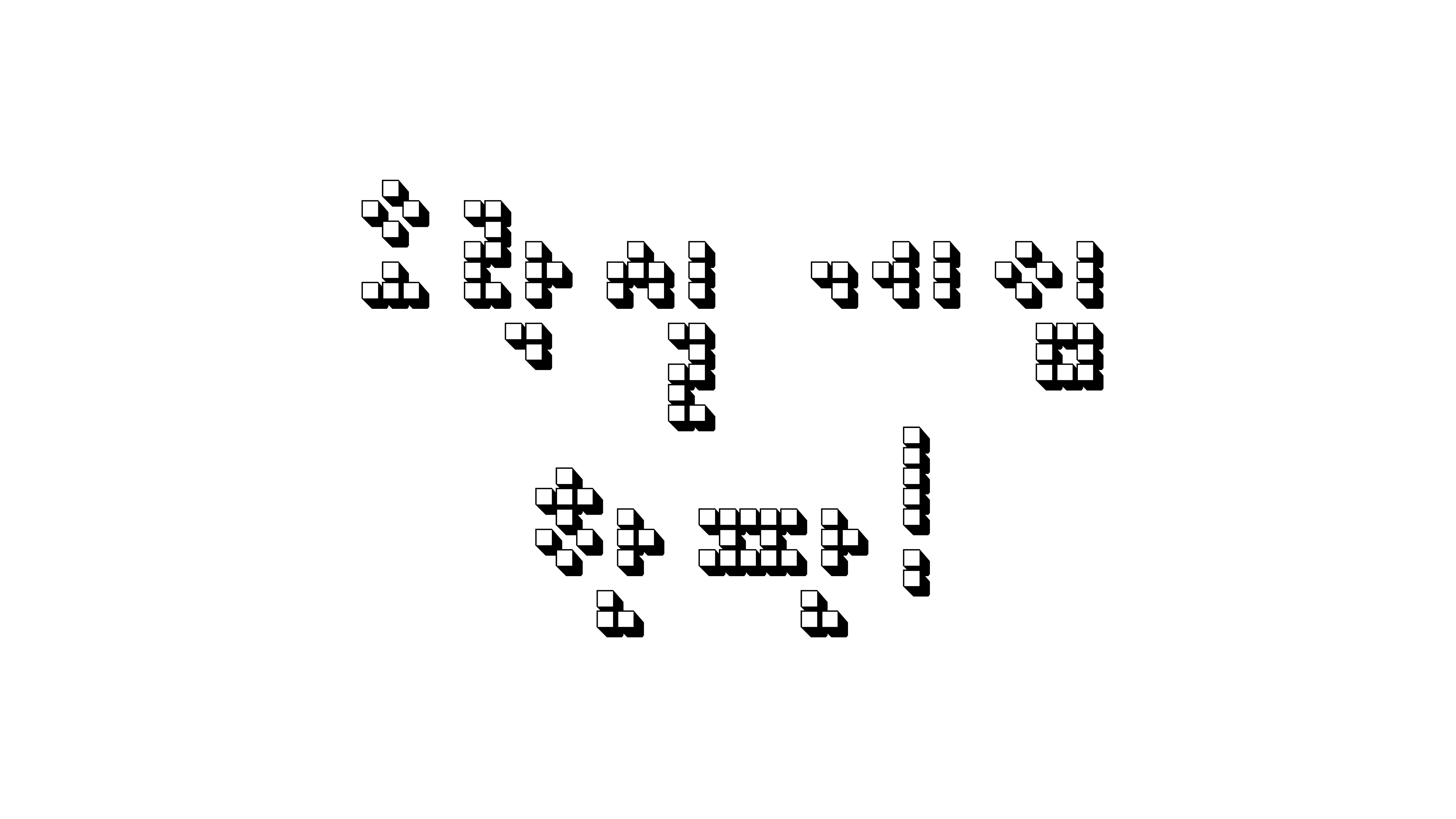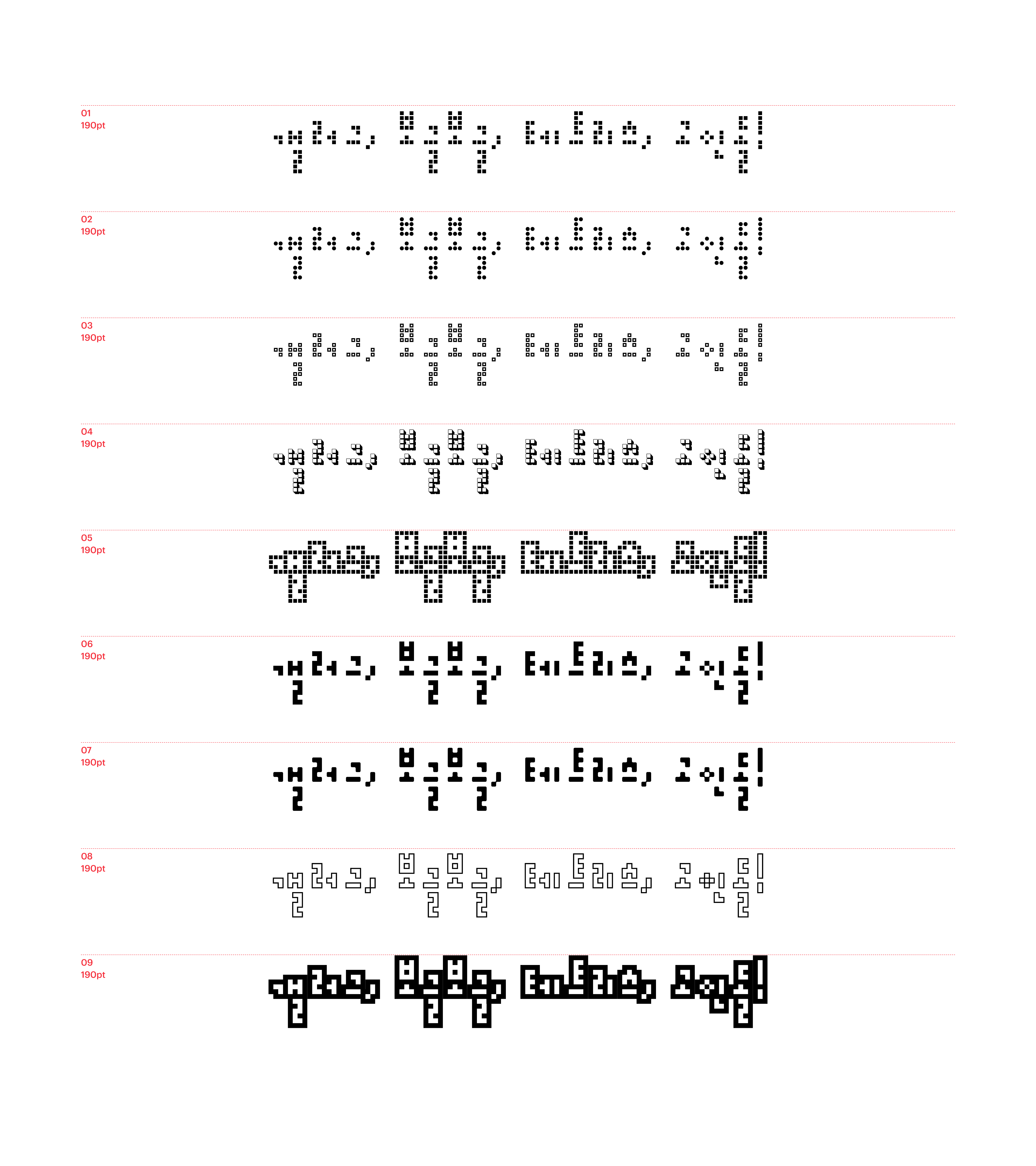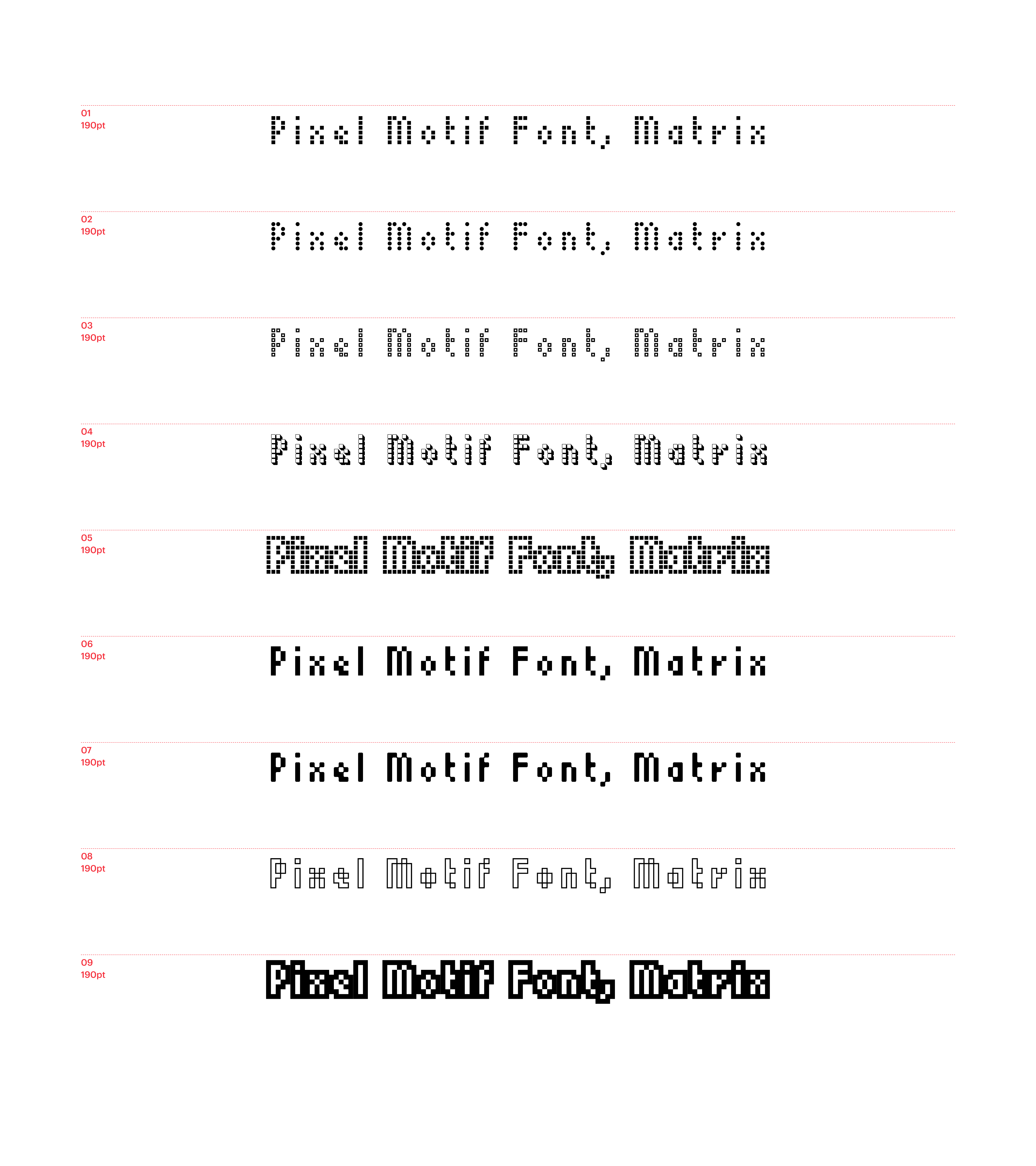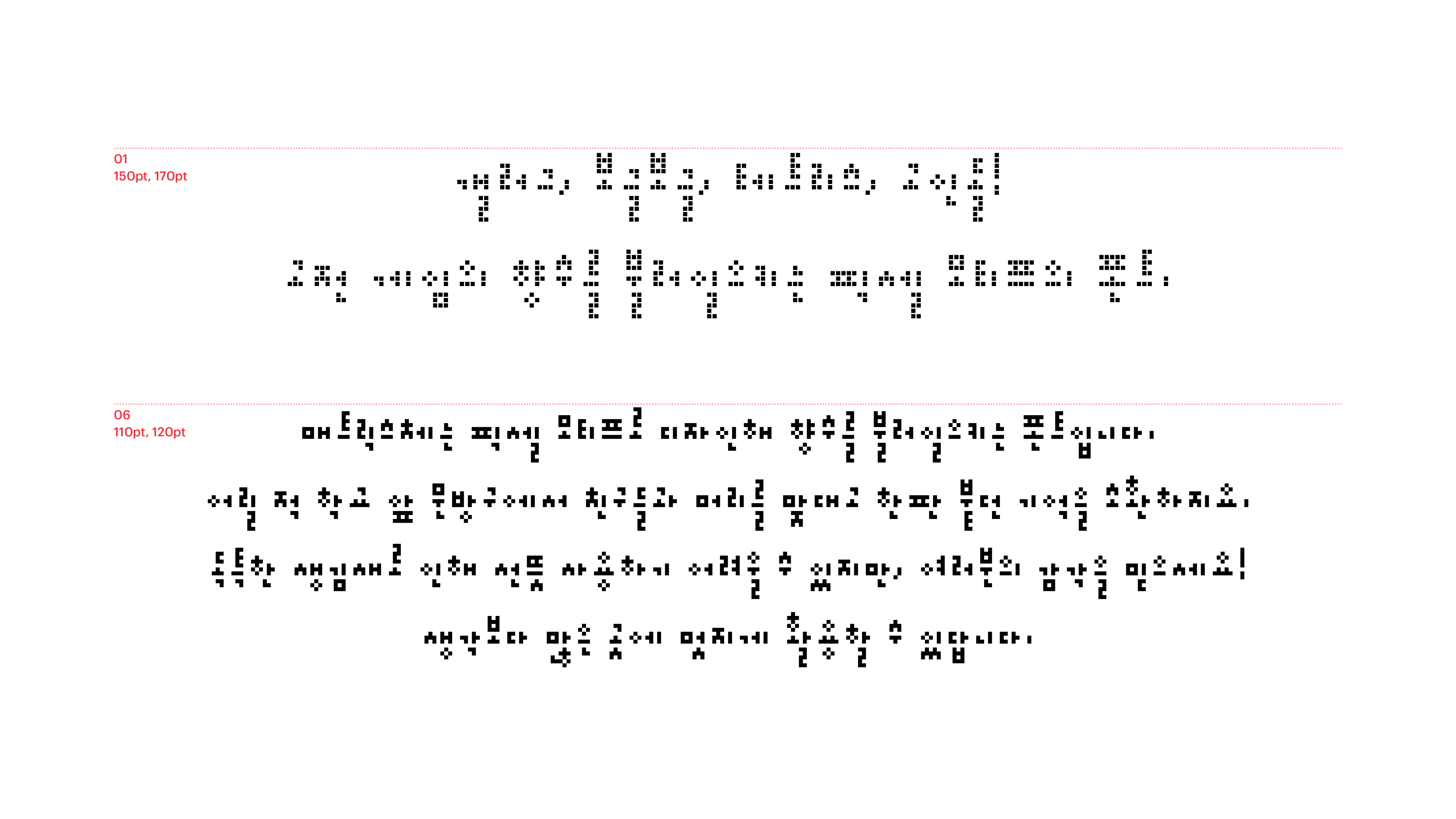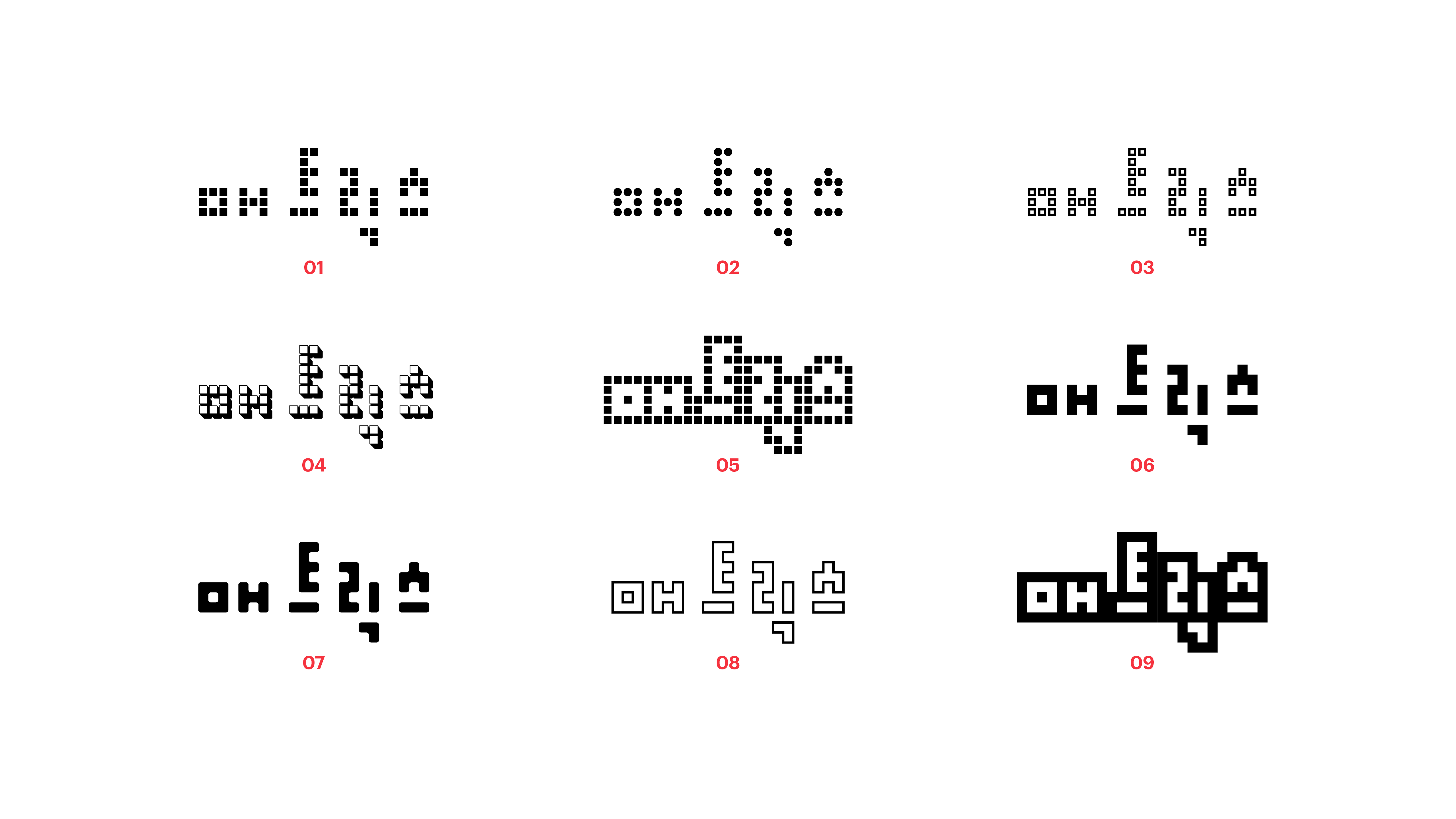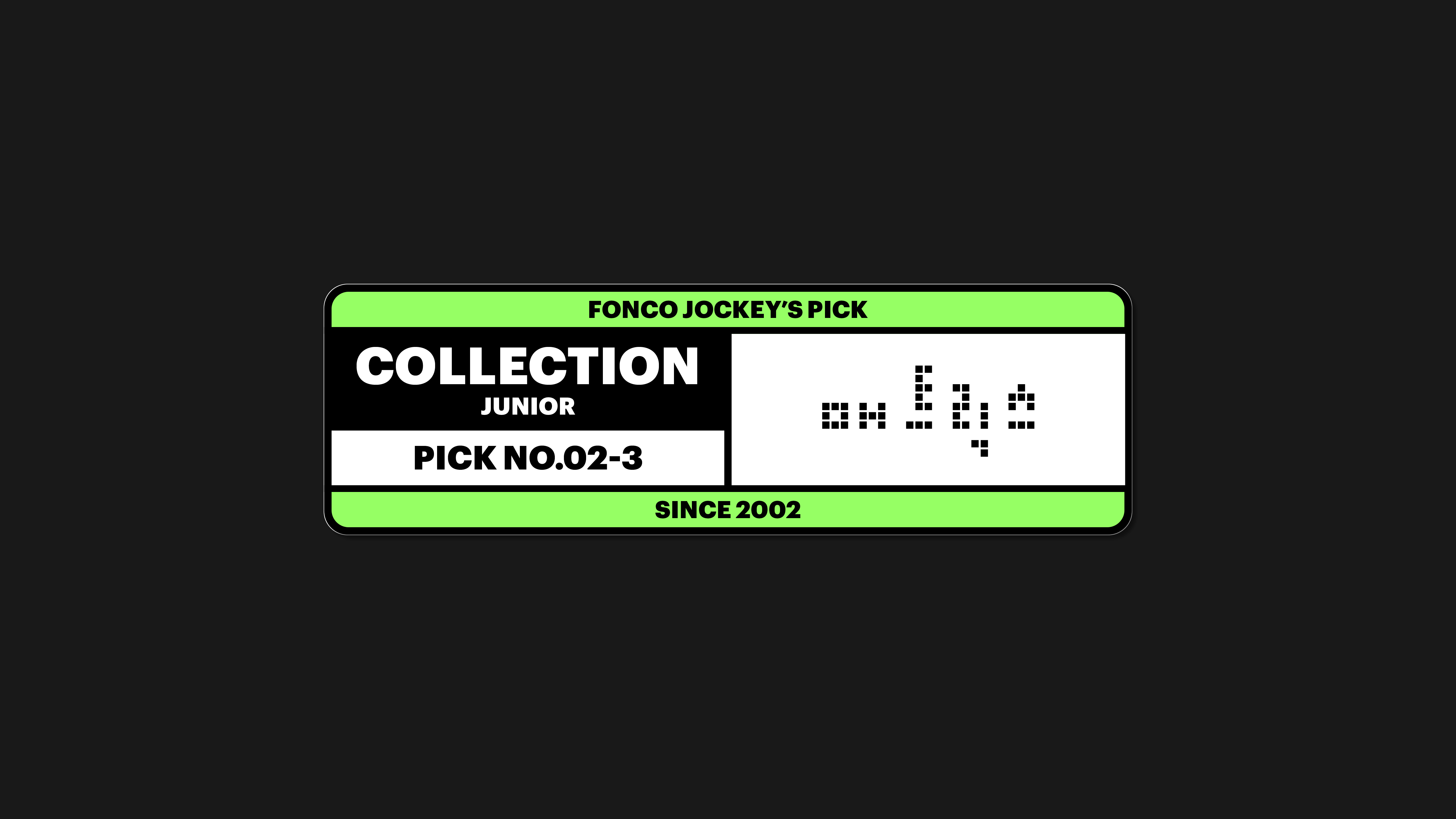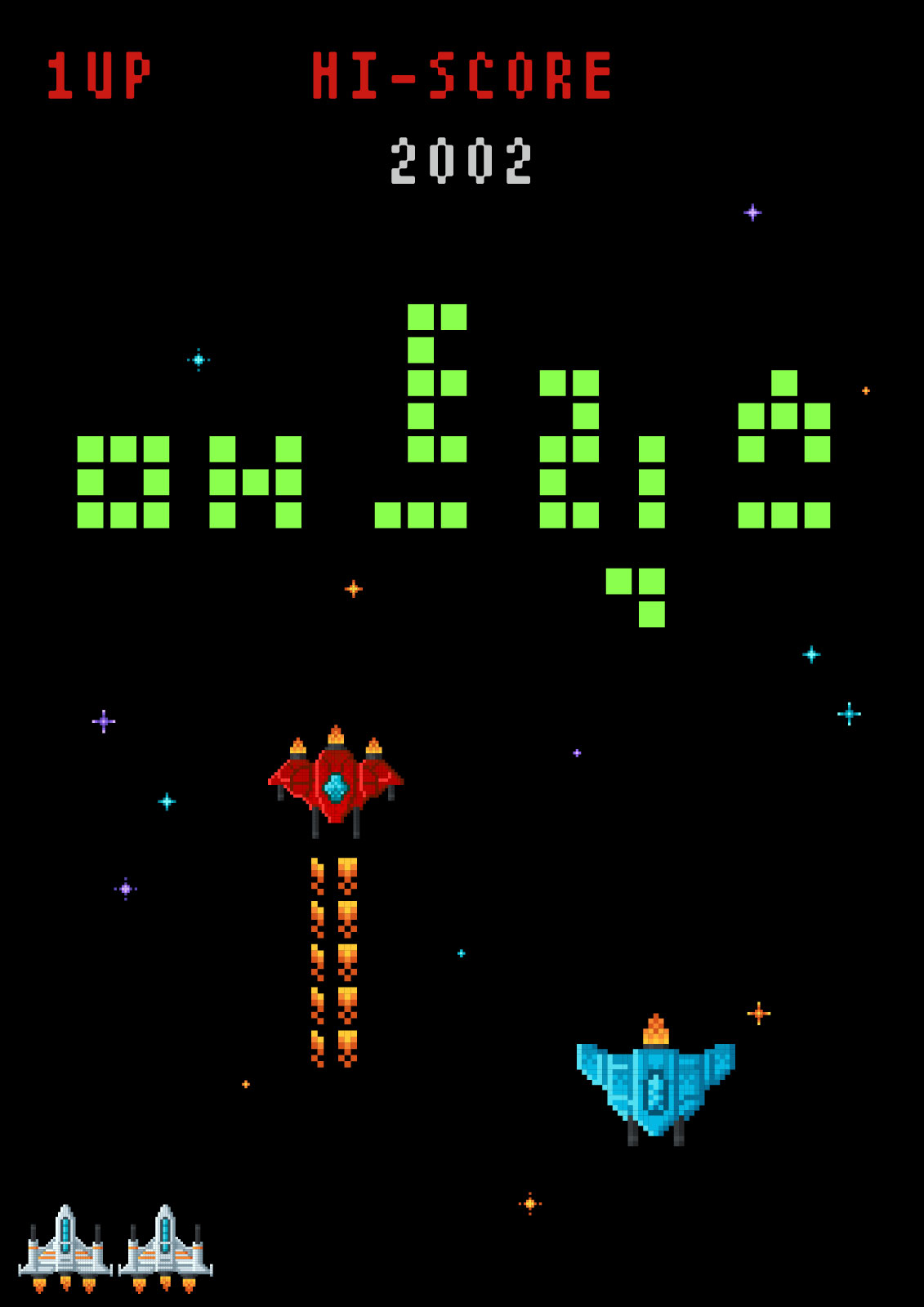
매트릭스
Yoon 매트릭스
매트릭스체는 픽셀 모티프로 디자인해 향수를 불러일으키는 폰트입니다. 어릴 적 학교 앞 문방구에서 친구들과 머리를 맞대고 한 판 붙던 기억을 소환하지요. 독특한 생김새로 인해 선뜻 사용하기 어려울 수 있지만, 여러분의 감각을 믿으세요! 생각보다 많은 곳에 멋지게 활용할 수 있답니다.